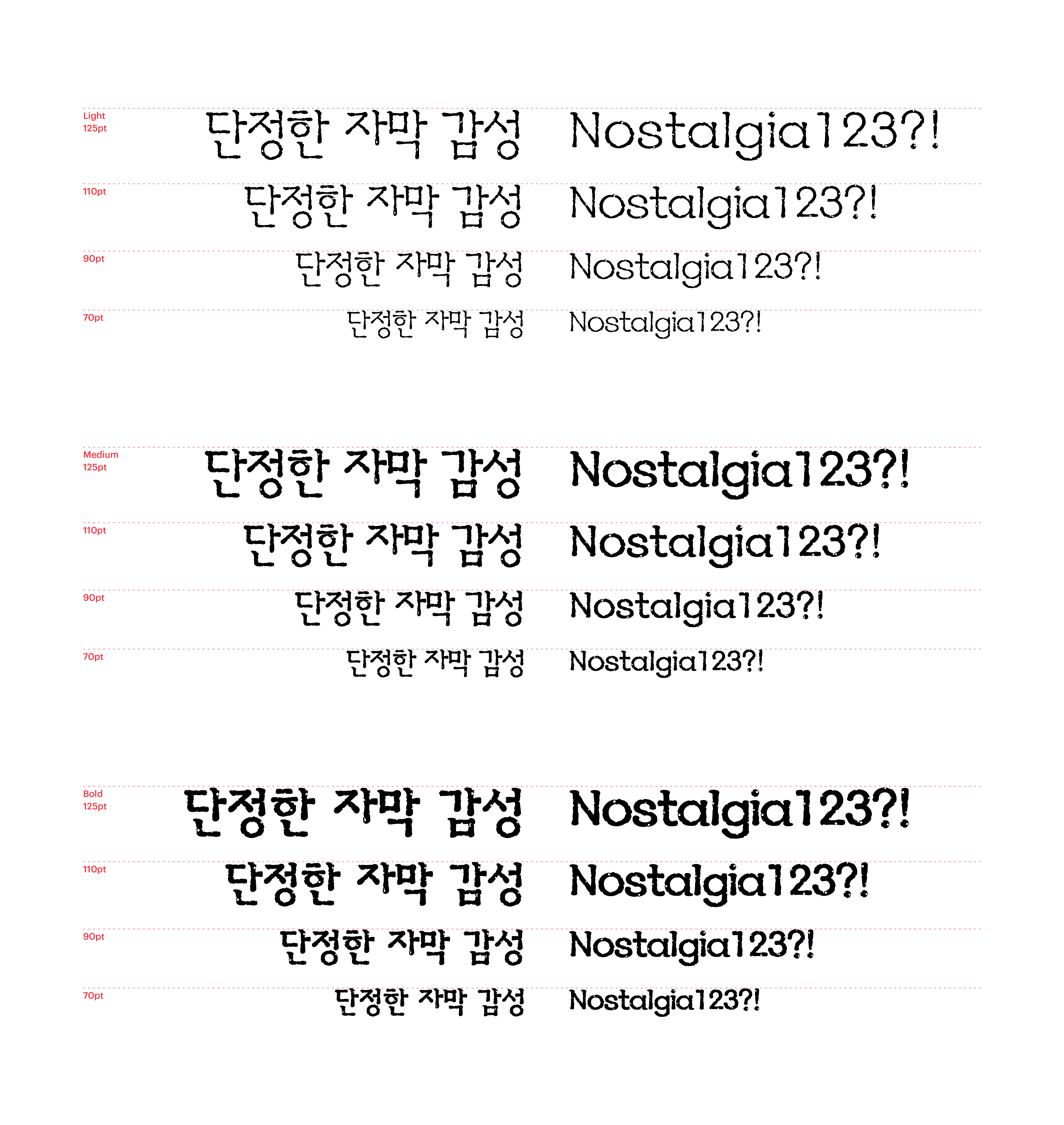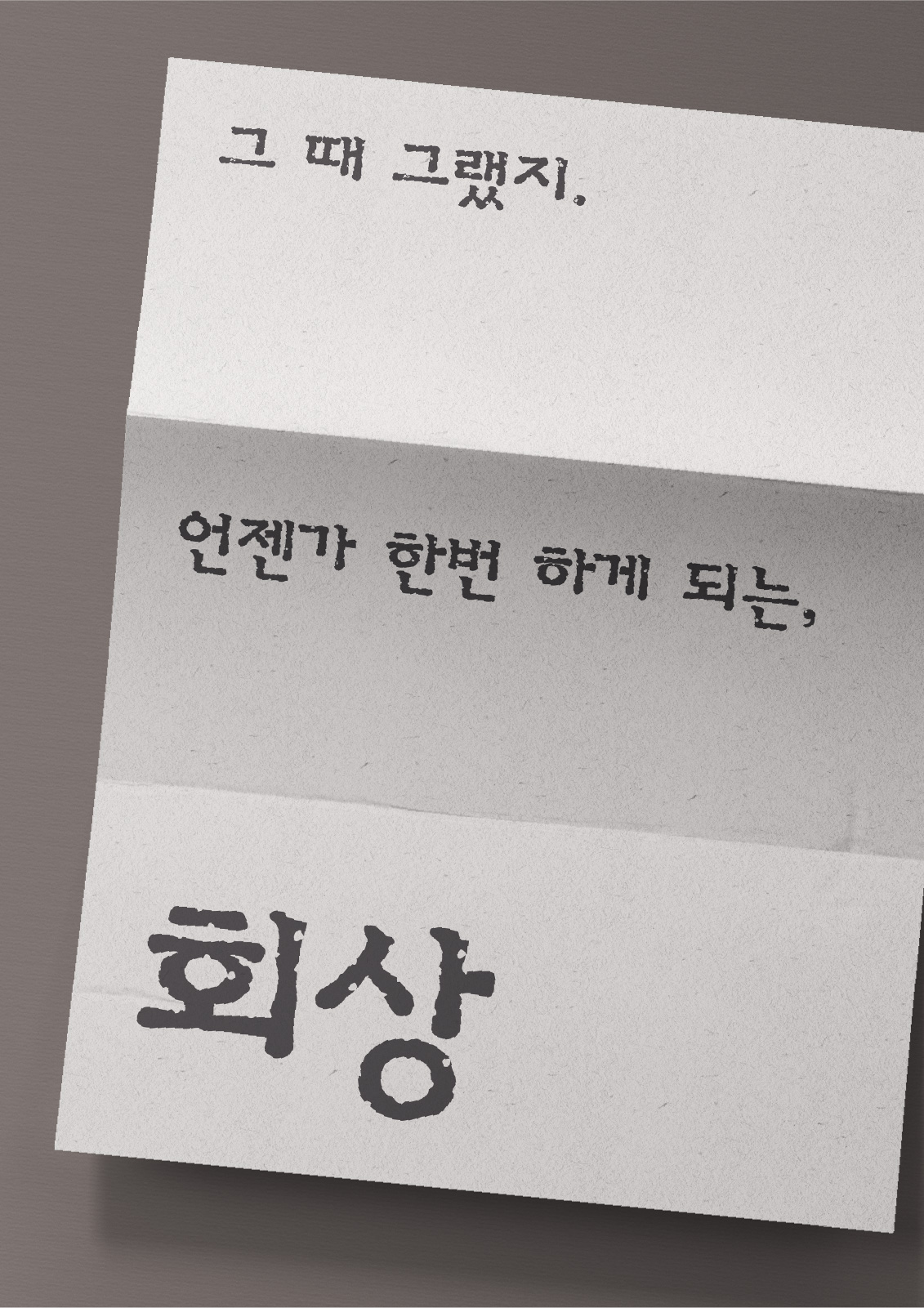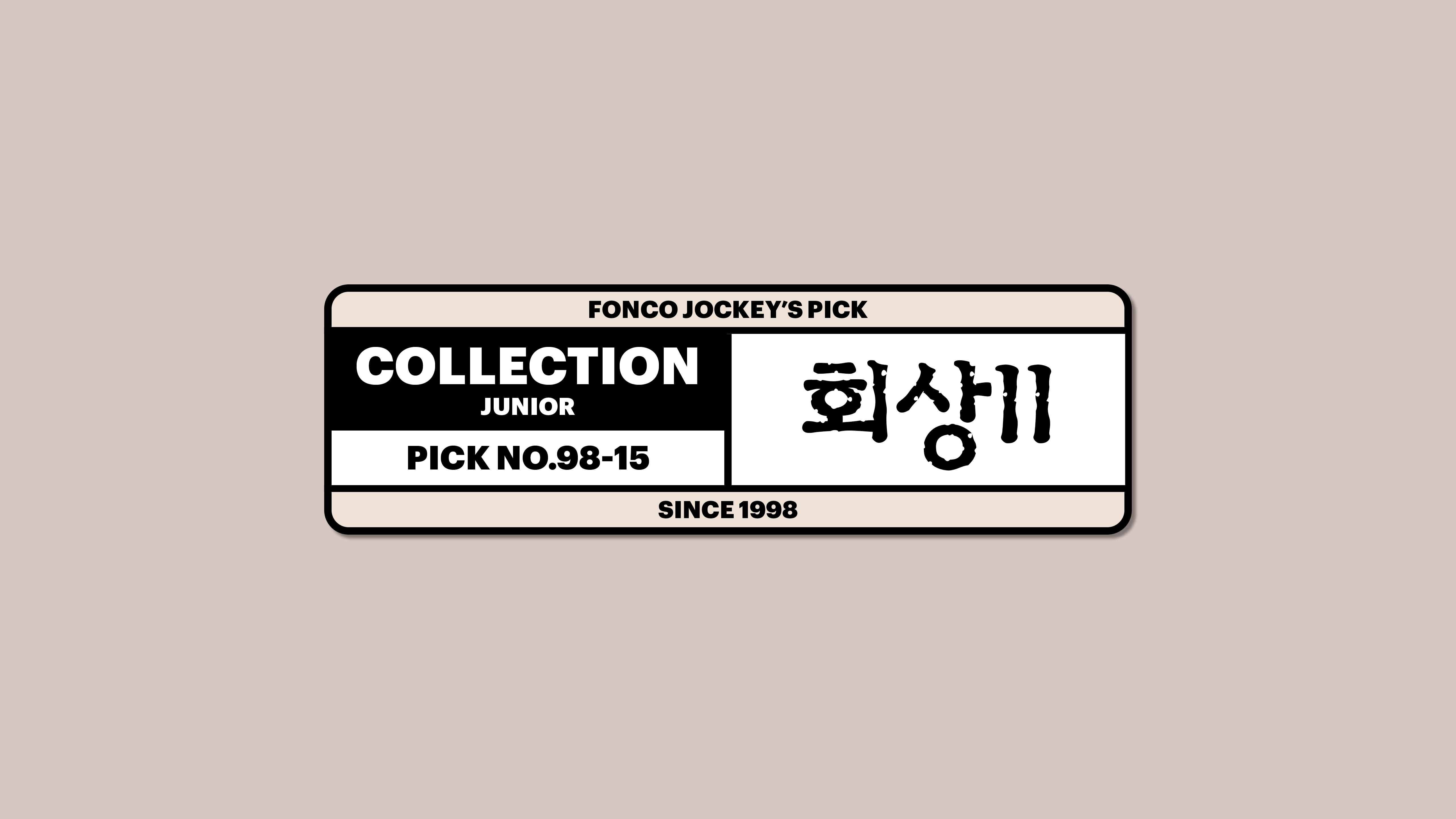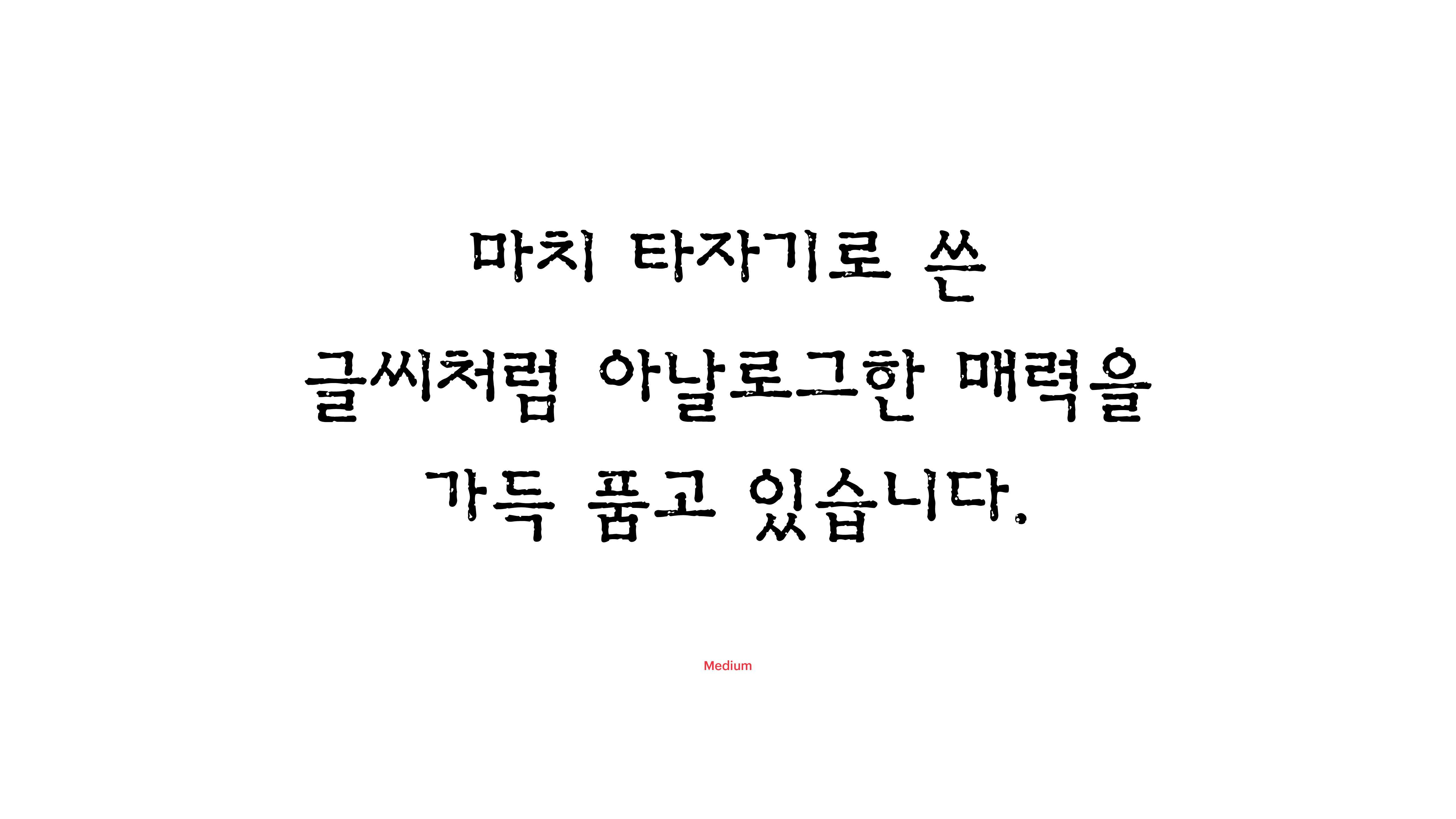
회상II
Yoon 회상II
과거를 떠올리는 장면 위에 가만히 올라 앉는 단정한 자막의 감성. 회상II체는 마치 타자기로 쓴 글씨처럼 아날로그한 매력을 가득 품고 있습니다. 그러니 회상II체로 무언가를 적을 때는 조심해야 해요. 나도 모르게 과거로 훌쩍 시간 여행을 떠나 돌아오지 못할 수도 있으니까요.